一代传奇---Helvetica
首先登场的便是大名鼎鼎的Helvetica,苹果、三星、英特尔、无印良品、宝马、汉莎航空、雀巢、Jeep等各大世界级知名品牌都不约而同选择其作为Logo字体,缔造了一个时代的字体传奇。
Helvetica诞生于20世纪五六十年代的瑞士。1955年,为了对抗当时欧洲卖的最好的字体Akzidenz Grotesk,瑞士哈斯铸字厂请来了身兼销售和设计的马克斯·米耶丁格和设计师德华德·霍夫曼,他们一起设计出了一款新的字体“New Haas Grotesk”,缩短了字母之间的间距,使文字更简洁大方、可读性也更强。在随后的1957年“平面57”博览会上,这款字体吸引了各大企业的关注。为了New Haas Grotesk更加国际化,哈斯铸字厂又用拉丁文‘瑞士’的单词为其命名,即Helvetica,并沿用至今。
Helvetica横扫字体领域的原因在于其圆滑流畅的中性感、阅读体验极佳,初看起来毫无特色,却能毫不违和的运用于各个场景领域。
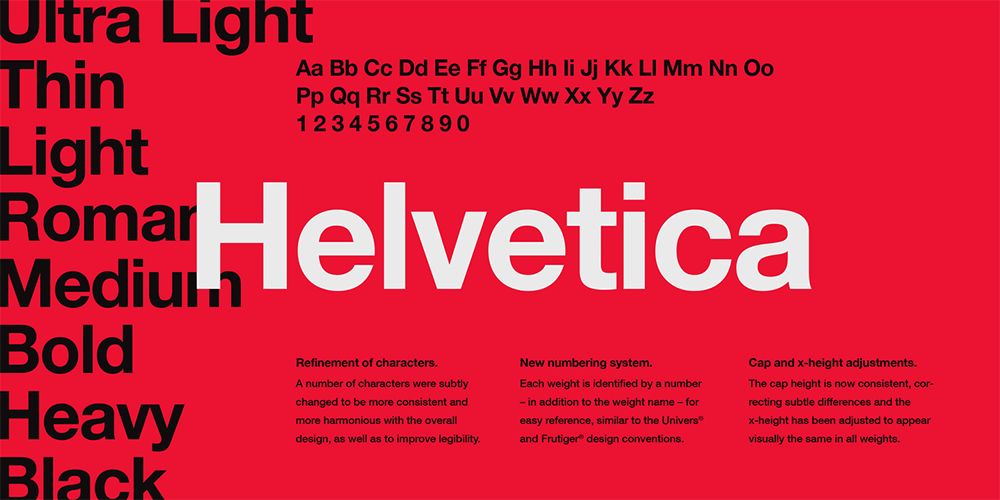
20世纪六七十年代,Helvetica几乎横扫全世界使用拉丁字母的国家。1962年,德国平面设计大师奥托·艾舍在为汉莎航空公司设计新Logo时,果断选择了Helvetica,从此更是名声大噪。进入计算机时代,1985年苹果公司将Helvetica装入其系统中,更使其影响力达到了登峰造极的程度,有数百家跨国企业甚至政府机构都直接采用Helvetica作为标识文字。
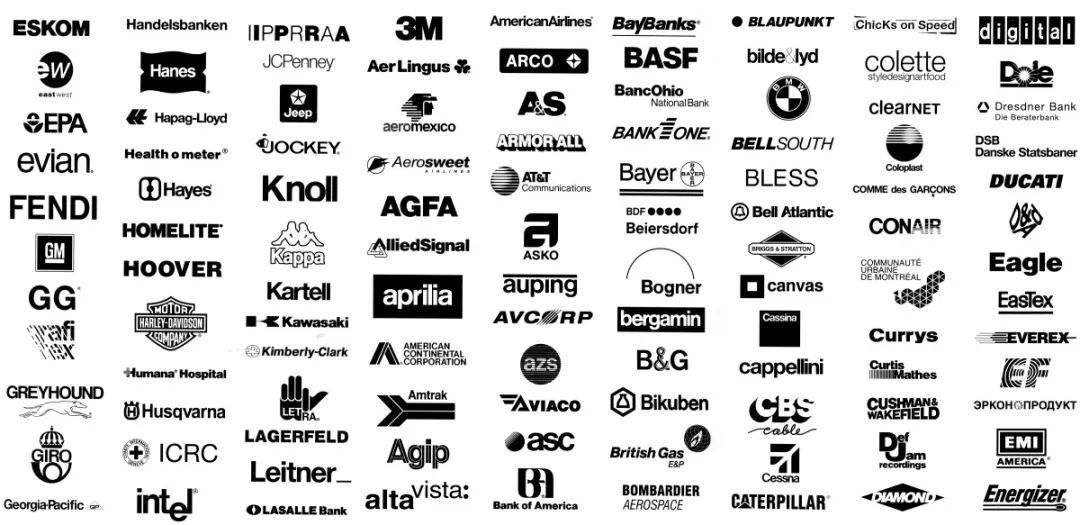
Helvetica如今已走过半个多世纪,跨越了活字印刷到移动互联网时代,以其惊人的适应性顺应着不同时期的设计潮流,依旧让全世界的设计师、企业家、字体爱好者为之着迷。
低调的典雅---Times New Roman
Times New Roman多用于报纸杂志等印刷媒介,诞生于20世纪三十年代,设计者名叫斯坦利·莫里森。
莫里森是一位很有脾气的设计师,他认为英国《泰晤士报》的字体丑陋又过时,于是写信给报社编辑,毛遂自荐设计一套新字体。而《泰晤士报》也展现了主流大报的胸襟,他们虚心接受了莫里森的建议,并邀请他设计一款全新的字体。
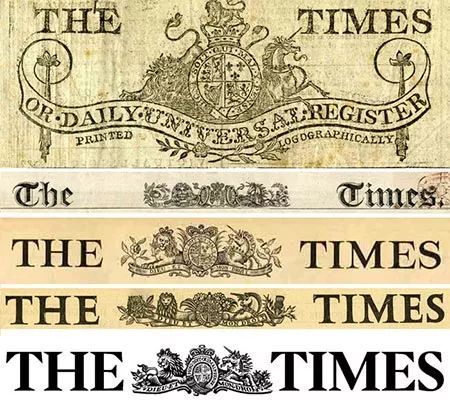
莫里森钟爱两千多年前古罗马的字体风格,他认为奥古斯都时代创造的拉丁字母是无法超越的巅峰。最终他选择了16世纪的Plantin字体为设计风格的基础。
1932年,新设计的字体闪亮登场。泰晤士报的英文名是The Times,之前用的字体为Times Old Roman,于是新字体就被命名为Times New Roman。
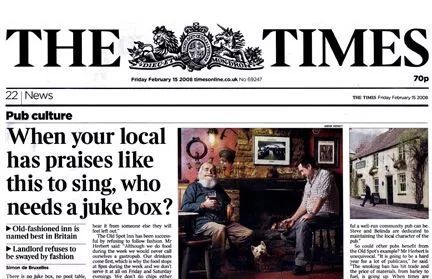
莫里森在Plantin字体的基础上缩小了Times New Roman的字间距,却保留了其美感和易读性,使泰晤士报每一版都可以印刷更多篇幅,但看起来一点不拥挤,即使印刷很小的字也能保证读者阅读起来毫无压力。
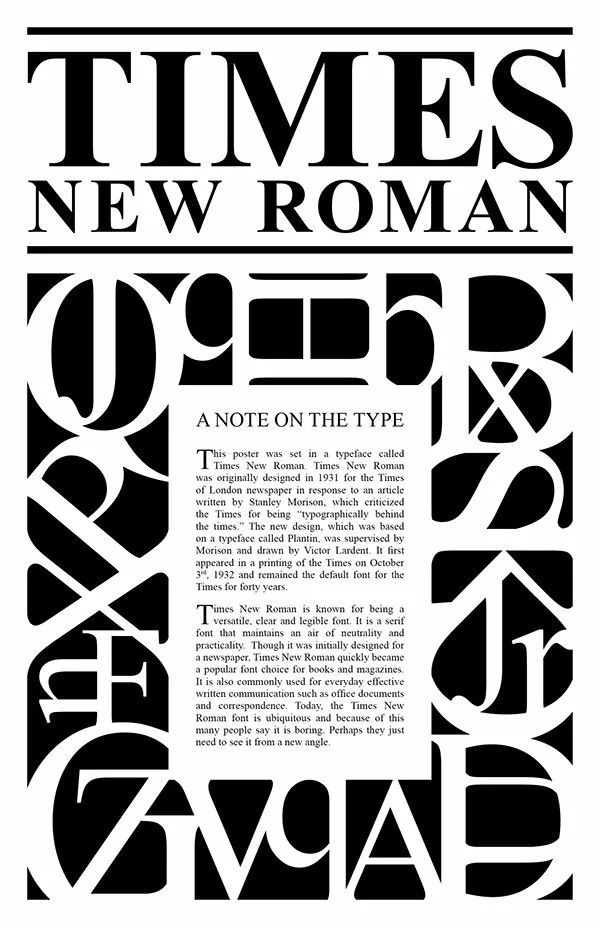
Times New Roman一经问世便一炮而红,成为所有杂志、书籍印刷的首选字体。到了20世纪90年代,微软将Times New Roman选为Windows系统的默认字体,伴随其如日中天的影响力,Times New Roman的知名度也遍及全球。迄今在图书、互联网、杂志、电视等媒介都能见到其活跃的身影。虽然不像Helvetica在品牌识别领域特别受到青睐,却始终保持其独有的风范,经济实用、清晰易读、低调中蕴含着典雅之美。
时尚界的宠儿---Didot
前文介绍的Helvetica和Times New Roman,虽然在字体界都具有不可小觑的地位,却始终入不了时尚圈的法眼,可见顶级时尚品牌对于字体选择严苛到了何种程度。提到时尚品牌的Logo字体,就不得不提Didot,其从诞生之日就站在时尚潮流尖端、备受大牌宠爱。
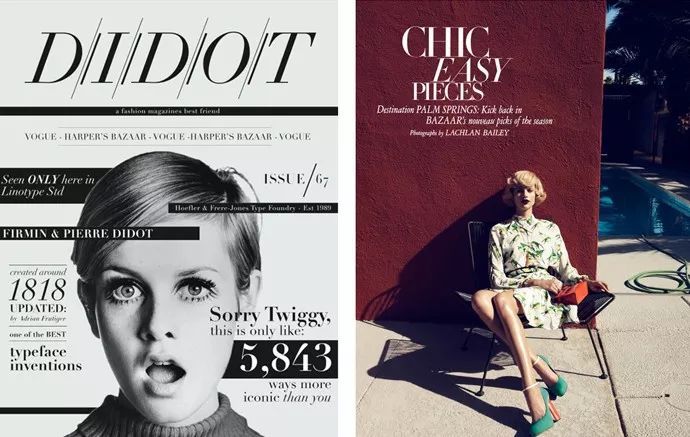
Didot字体源于法国Didot家族,具有三百多年的悠久历史。伴随着启蒙思想和工业革命对社会生产的影响,Didot字体被自然的引入到时尚产品的洪流中。它最大的特点是强烈的粗细对比和锋利的衬线,看上去更为庄严冷峻,如同骄傲纤长的法国人。在许多高端定位人群的杂志中很受钟爱,显得高级、品质感十足,这其中最具代表性的就是时装杂志《VOGUE》。
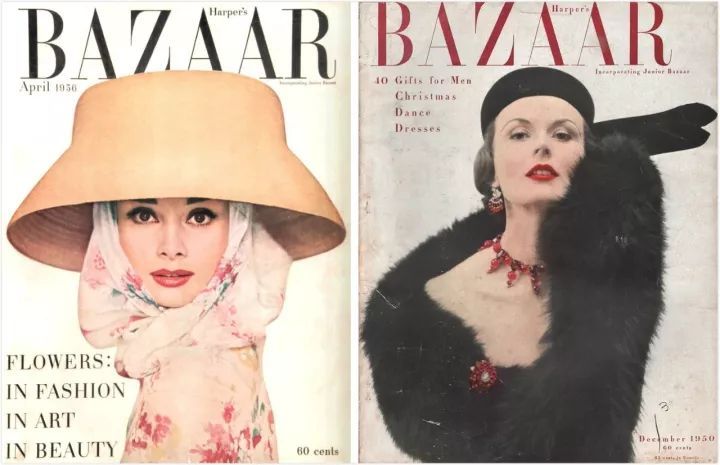
创刊于1892年的《VOGUE》,目前已在21个国家发行,被封为Fashion Bible。而Didot是《VOGUE》一直以来的御用字体,即使主编换了又换,字体的地位从未动摇。就连之后1945年创刊的《ELLE》杂志,也不能免俗而选择Didot smile字体。
不仅仅是高端时尚杂志,众多奢侈品牌也是Didot的忠实拥护者,比如Giorgio Armani、Burberry都以Didot字体为Logo设计的原型。
历经两个多世纪的洗礼,Didot已成为时尚工业的重要组成部分之一。它诞生于动荡中的法国,以其独有的字体表现力永远留存在了法国乃至全世界时尚界的基因之中,成为了永恒的经典。
未来先锋---Futura
近年来,随着互联网让世界变得越来越扁平,越来越年轻化的时候,很多传统大牌将自己的品牌LOGO纷纷改为无衬线字体。如美国时装品牌凯文克莱Calvin Klein、以及奢华鞋履定制品牌威士顿(J. M. Weston)等。众多无衬线字体家族中,Futura又受到格外青睐。
Futura诞生于1927年,和Helvetica一样同属无衬线体,也同为现代主义的产物。但设计师保罗伦纳创造的Futura字如其名,更具未来感,舍弃了一切不必要、时髦的装饰元素,菱角分明的几何感是其最强烈的特征。
比如字母V和N的转折非常锋利,丝毫不拖泥带水,又比如字母O看上去“几乎”是一个正圆。
Futura第一次为世人瞩目是被美国航空航天局NASA垂青,成为阿波罗11号宇航员留在外太空的一张字母雕刻的铭牌,极具科幻感。加上其基于传统罗马比例和未来主义之间的字体风格,日后又深受电影圈大佬的喜爱。
Futura代表了一个时代的进取精神,它清晰干净的视觉表现力让很多企业主为之狂热。正如20世纪五六十年代的大众汽车,Futura一度代表了大众面向未来、与工业时代接轨的形象。
而在时尚界,Futura的大名更是如雷贯耳。如我们熟悉的奢侈品品牌LV,商标完全用的Futura并且没有大的改动,只是增加了字间距,去营造属于lv的品牌气质,威严和霸气。
还有杜嘉班纳,和lv不同,它的品牌想传达的不是lv那种厚重感,而是一种年轻的都市感,所以他把商标排的很紧凑,更加活泼和独立。不论是年轻化的运动品牌,还是走高端路线的奢侈品牌Futura都应对自如,特有的几何性让品牌显得高级而冷峻。
就连Google也抗拒不了Futura,在2015年做了17年以来品牌字体最大的一次调整,是基于Futura的新字体设计。
从1927年直到今天Futura迎来了70岁的生日。当年恃才傲物的Paul Renner也正如他的宣言让Futura成为独一无二的字体,备受世界的追捧。